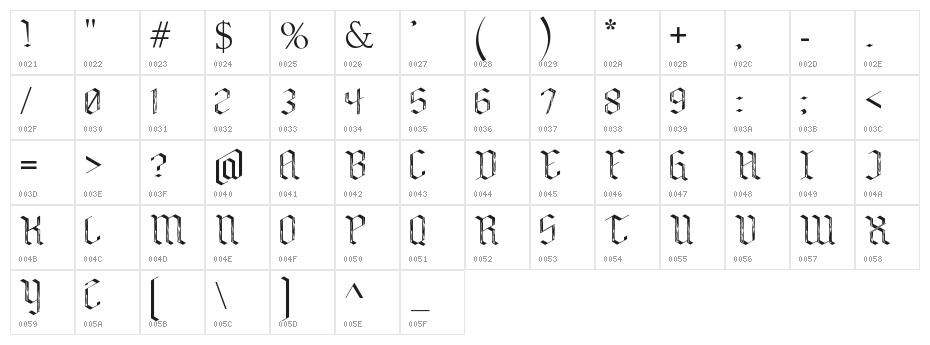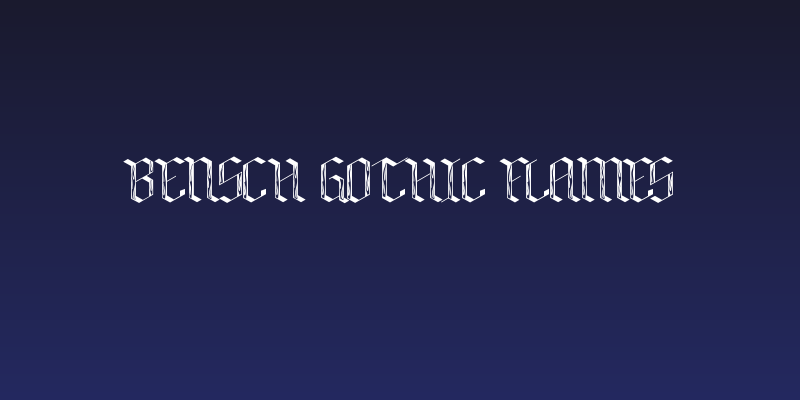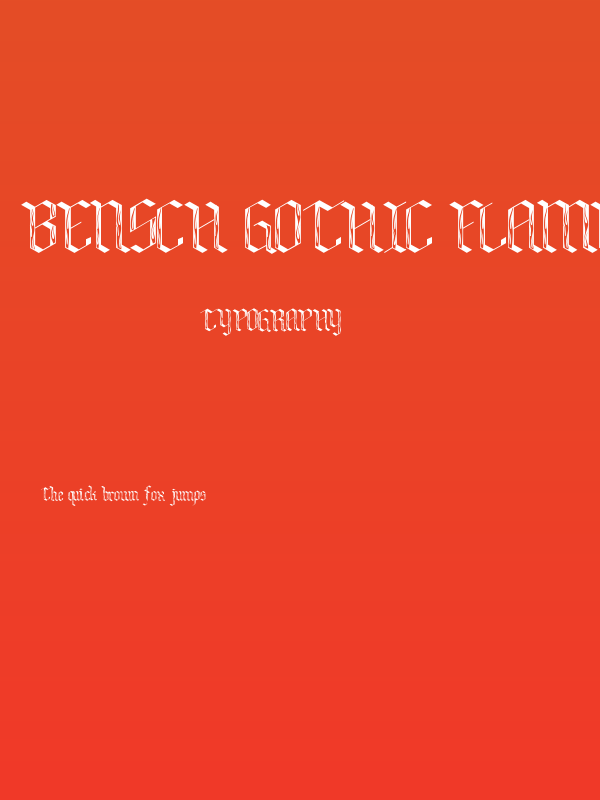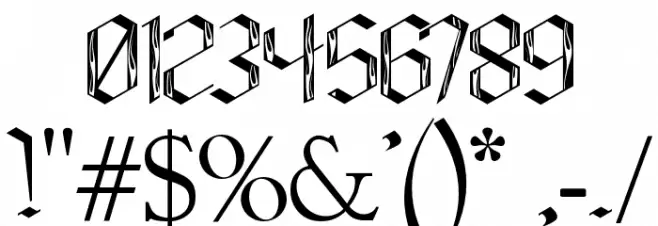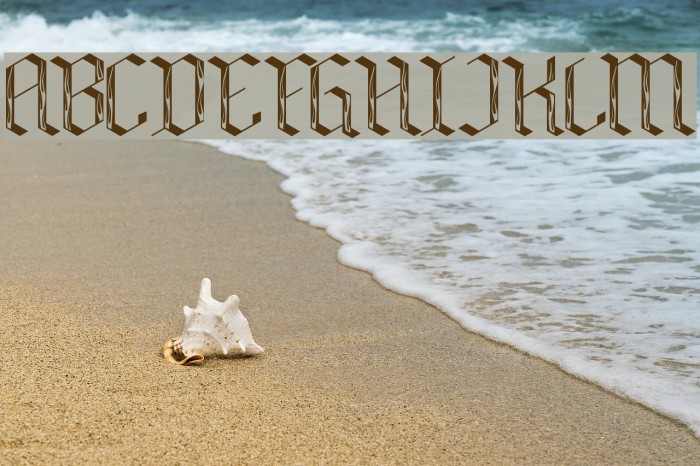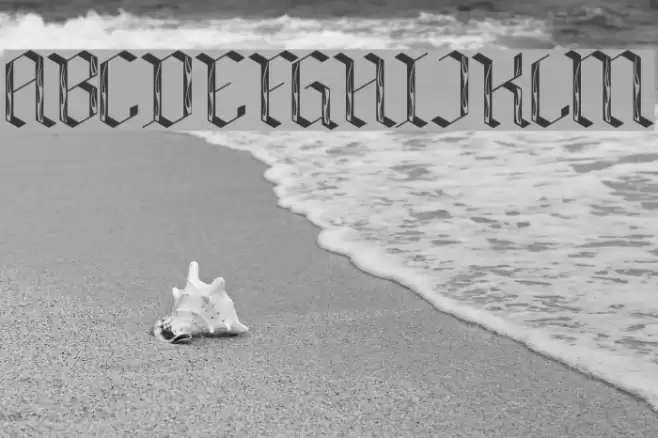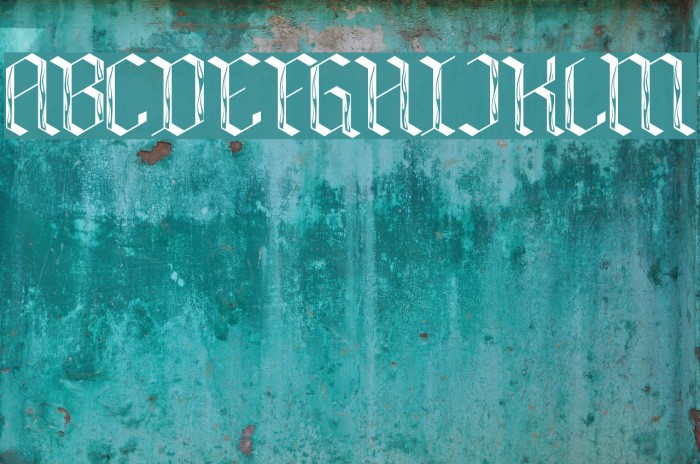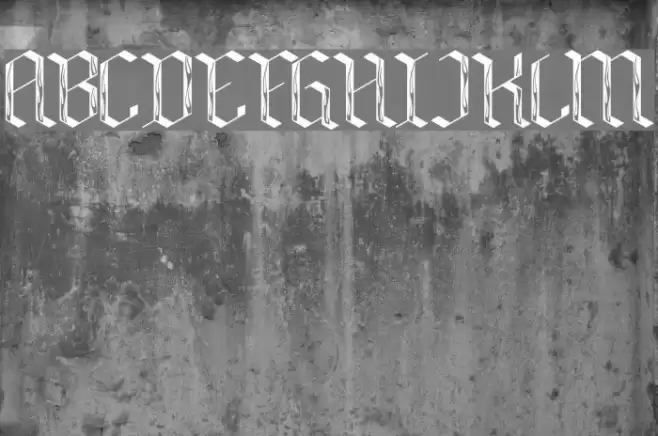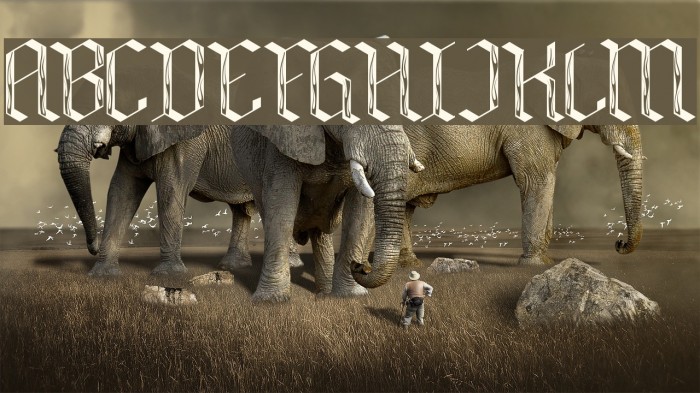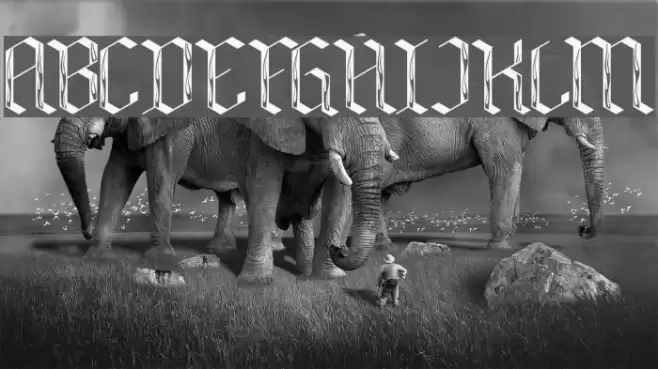
Bensch Gothic Flames Font
| Progetti proposti | Ideal for projects needing a dramatic and eye-catching typeface, such as posters, album covers, or themed event invitations. |